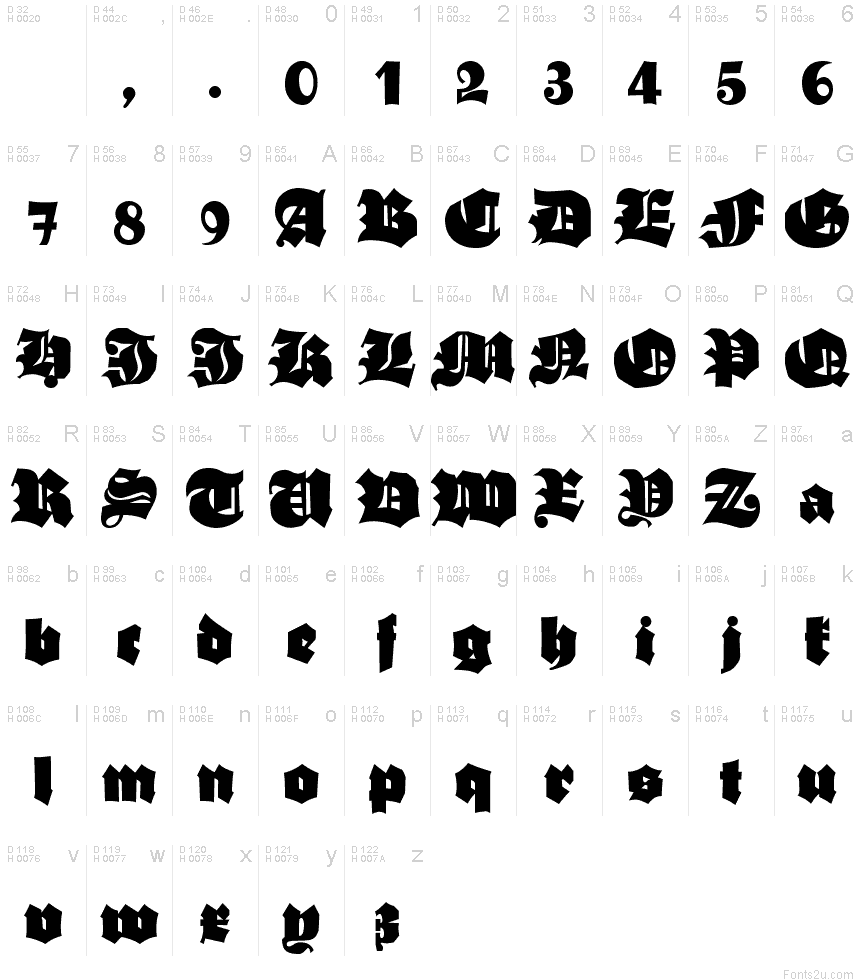
AsgardianWars Black autorstwa Andrew Forrestera to darmowy gotycki krój pisma, który uderza z siłą młota bojowego. Masywne pociągnięcia w stylu blackletter, postrzępione kąty i ostre ostrogi sprawiają, że każde słowo przypomina wyryte w kamieniu znaki lub sztandary z pól bitewnych. Litery łączą się w zwartą, niemal murarską teksturę, nadając nagłówkom dziki, starożytny i bezkompromisowy charakter.
Za pomocą AsgardianWars Black możesz wyczarować mroczne światy fantasy na okładkach książek, logotypach zespołów metalowych, podręcznikach RPG, tytułach gier, plakatach tematycznych czy grafikach inspirowanych tatuażem. Ten darmowy font najlepiej sprawdza się w dużych rozmiarach, gdzie jego ciężkie krzywizny i kolce mogą w pełni wybrzmieć. Zestaw go z wąskim, czystym krojem bezszeryfowym w mniejszym tekście, aby zachować czytelność, podczas gdy rodzina AsgardianWars dostarczy całą dawkę dramatyzmu.